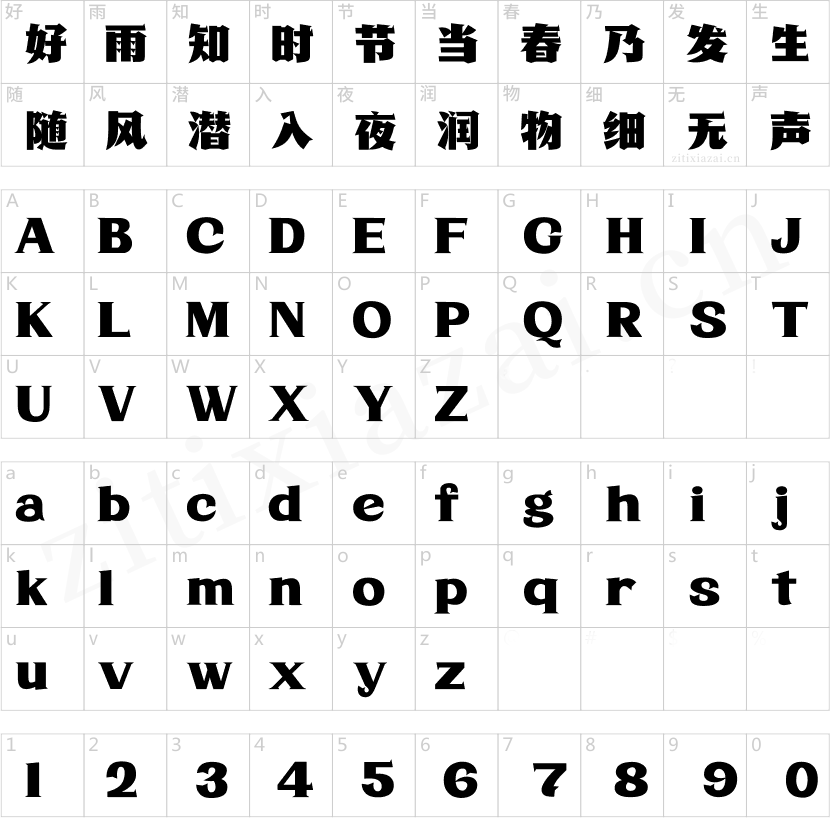
Aa动员宋
Aa动员宋,这款字体结构工整、笔画清晰,兼顾美观与易读性,适用于标题、正文、海报、包装、LOGO 等多种场景。字形优雅稳定,风格百搭耐看,适配日常排版与创意设计,让文字呈现更舒适、更具质感。Aa动员宋一笔一画,皆是细节,以均衡的比例、流畅的线条打造舒适视觉体验,字形端正大气,风格简约现代。无论是商业设计、品牌宣传还是日常排版,都能轻松驾驭,让文字更有格调与力量。Aa动员宋字体下载。
Aa动员宋是一款非常具有艺术性的字体,它的设计灵感来源于对古典艺术的研究,同时又融入了现代字体设计的元素。字形优美,笔画粗细变化自然,给人以大气、典雅的感觉。Aa动员宋是一款既传统又现代的字体,它的设计充满艺术感,美观大方,实用性也非常强。无论是对于设计师还是对于普通读者来说,都是一种非常不错的字体选择。Aa动员宋适合用于具有艺术感的场合,比如海报、宣传单张、书籍封面等。由于其字形流畅且具有动态感,也适合用于大量的文本排版,如报纸、杂志等。
• 字体名称:Aa动员宋
• 字体全名:Aa动员宋